Hace poco recibí un encargo para hacer unos letterings de pizarra para decorar un bar, aproveché para hacer fotos mientras los hacía y hoy te cuento cómo puedes hacer tus propios lettering estilo chalk.
El post se llama cómo hacer un falso lettering de pizarra porque en realidad no vamos a usar una pizarra y tampoco tizas 😉
Materiales cartel falso Chalk Lettering
Los materiales que vas a necesitar para hacer tu cartel tipo lettering de pizarra son:
- Lápiz y goma de borrar.
- Regla (por si necesitas medir).
- Rotulador Posca blanco (opcional).
- Rotulador Uni Chalk marker blanco.
- Cartón pluma negro.
Tutorial Chalk Lettering
Las ideas
Cuando tengo que hacer un lettering para un encargo, siempre empiezo haciendo unos bocetos para que el cliente tenga varias opciones donde elegir.
En este caso, el cliente era un bar que reabría con un cambio de imagen. Solicitaron un logo nuevo y un lettering para decorar la zona de la cafetera.
Opté por hacer los bocetos en cartulina negra y rotulador blanco para que se pudieran hacer una mejor idea de cuál sería el resulta final.
Una vez el cliente eligió el logo, empecé a trabajar en los letterings para que tuvieran el mismo estilo.
Bocetar
Empezamos bocetando el lettering con lápiz. Eso sí, no aprietes mucho el lápiz porque puedes dejar marcas.
Como superficie para hacer el lettering, en vez de una pizarra, hemos optado por el cartón pluma de color negro.
Nosotros usamos este pero lo encontrarás de distintos tamaños.
Lo bueno de usar el cartón pluma es que es muy ligero, fácil de colocar y perfecto para usar con rotuladores tipo chalk y lograr ese efecto de pizarra.
Repasar
Una vez tenemos el diseño bocetado con lápiz, repasamos con rotulador de color blanco.
Para esto hemos usado un rotulador posca blanco porque seca rápido y además prefiero repasar con una punta fina y después corregir por encima con el otro.
Pero si lo prefieres o no tienes este tipo de rotulador, puedes repasar directamente con el rotulador de tinta chalk.
Borrar
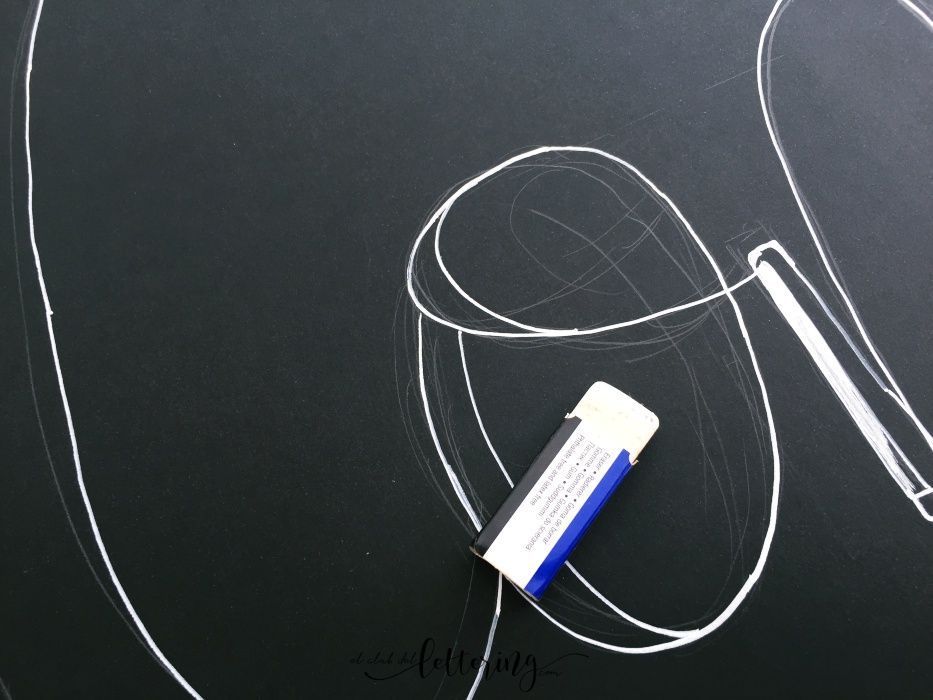
Cuando tenemos el diseño ya repasado, ya no necesitamos las lineas de lápiz que nos servían de guía, así que procedemos a borrar.
Ten cuidado y asegúrate de que la tinta se ha secado antes de borrar, sobretodo si has repasado con el rotulador chalk que tarda más en secar, porque de lo contrario se puede correr la tinta.
Rellenar
A continuación rellenamos las partes más gorditas de las letras usando un rotulador de tiza líquida.
Para este lettering hemos usado un rotulador Uni Chalk Marker blanco y nos ha ido genial.
La tinta es de tiza líquida y es muy cubriente, y la punta de 1.8mm-2.5mm nos sirven tanto para perfilar las partes más finas como para rellenar las más gruesas.
En la foto de abajo, puedes ver la diferencia de grosor entre los dos rotuladores. La linea más fina corresponde al rotulador Posca y la más gorda al Uni chalk marker.
Para el lettering de la zona de cafetera elegimos la frase: “L´hora del cafenet” (la hora del cafelito) y seguimos el mismo estilo que en el lettering del logo.
Para hacer el lettering, seguimos el mismo proceso: boceto, pasar el boceto a lápiz, perfilar, borrar, repasar y rellenar.
Una vez tenemos los letterings, echamos un último vistazo, rematamos y et voilà! así quedaron nuestros letterings ya colocados.